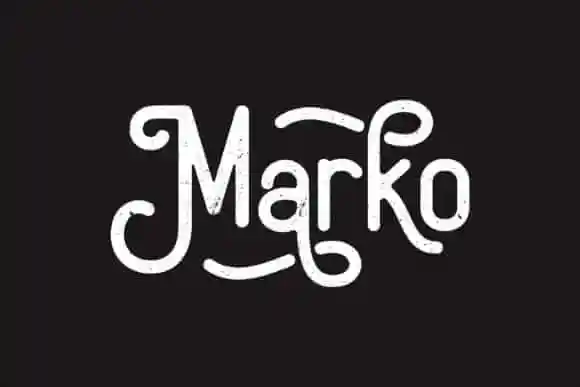
Marko Display Font
A Marko Display Font é uma seleção única de fontes display que transmite um toque vintage ao mesmo tempo que apresenta uma aparência moderna. Feito por um designer chamado Dickysyafaat, esta fonte oferece uma aparente versão dos anos 40, mas com seu próprio frescor e vitalidade que complementam os designs mais contemporâneos. Perfeito para a criação de logotipos, identificações de produtos, embalagens, marcas de água digital, posts nas redes sociais, materiais de vestuário, cartas de convite, sinalização, clubes esportivos, carros ou veículos e eventos especiais — ela pode ser usada para trazer um toque moderno aos designs mais tradicionais. Com Marko Display Font, você pode criar uma paleta visual que se destaca no mundo digital enquanto mantém seus projetos com um sabor nostálgico vibrante.